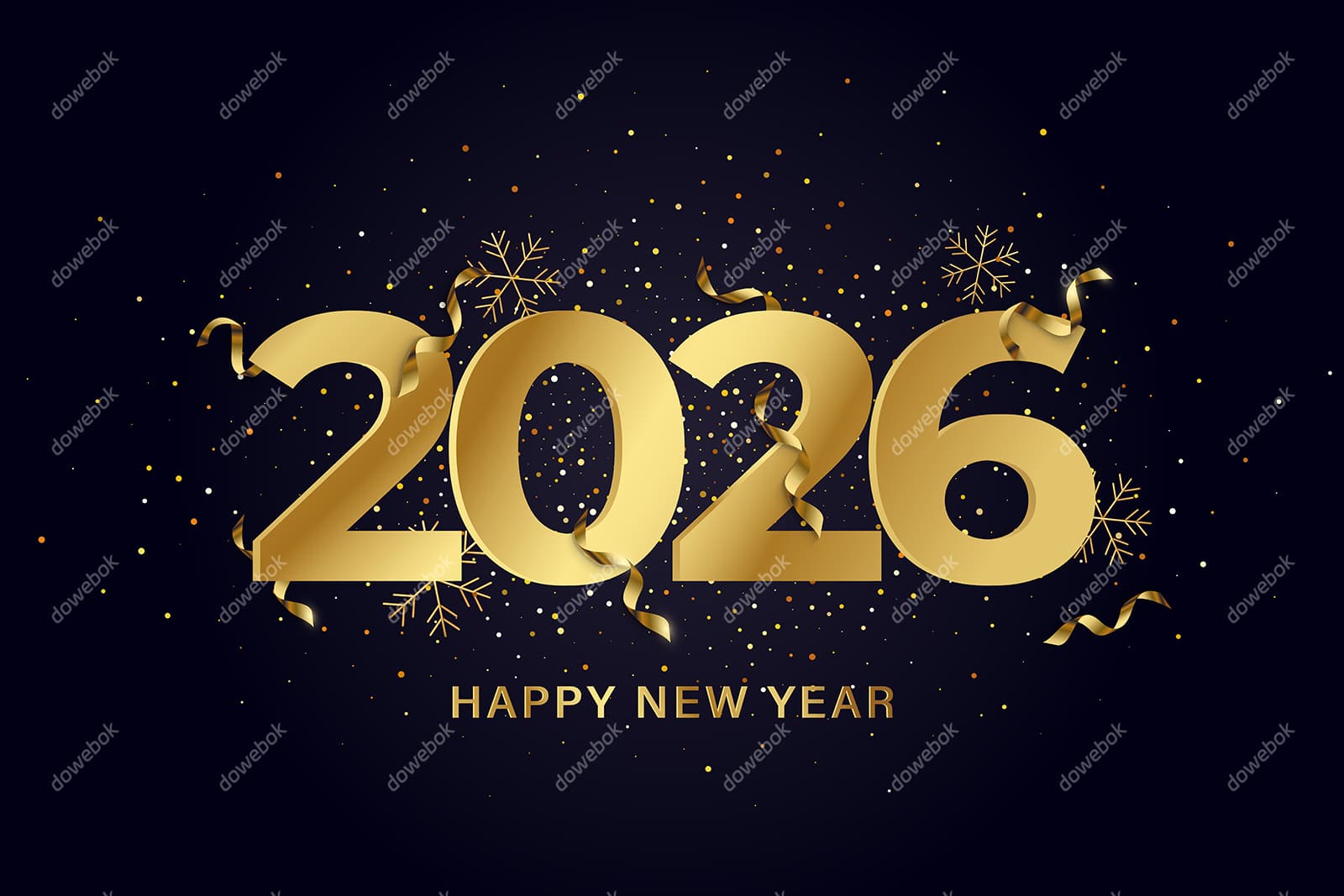
这是一款金色数字设计 2026 新年快乐矢量素材,深黑夜空铺着细碎金点,营造轻奢氛围感。金色立体 “2026” 字体光泽饱满,周围点缀雪花装饰与卷曲金彩带,灵动俏皮。下方配简约黑体 “Happy New Year”,整体以黑金配色 + 节日元素,既显雅致高级,又透出跨年的欢快与温馨,精致感与氛围感兼具。